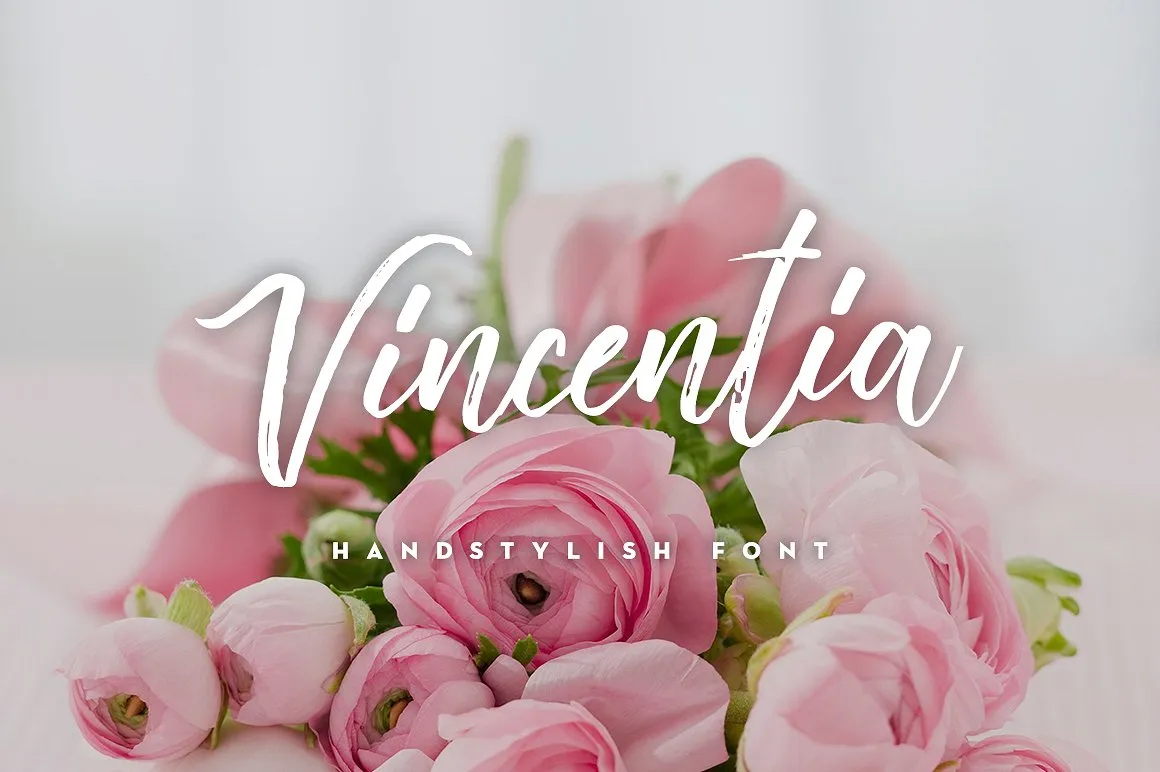
Vincentia Handstylish Font – Download Grátis
Vincentia Handstylish Font é uma nova adição à família de fontes brush do Alif Devan R., desenhada para atender a necessidades criativas. Ideal para logos, cabeçalhos, títulos e impressões, ela também se destaca para processos criativos em geral. Desenvolvida com um estilo autêntico e natural, Vincentia oferece uma textura única que torna qualquer projeto impecável. Com o uso de Vincentia Handstylish Font, você pode criar resultados extraordinários com um toque autoral incrível. Perfeita para aquelas idéias inovadoras que requerem uma cara única e alegre, ela é perfeitamente adequada para aqueles projetos que valorizam tanto a elegância quanto o design único da mão. Seja você um artista gráfico em busca de uma fonte única ou um designer profissional desejando dar um toque especial aos seus designs digitais, Vincentia Handstylish Font está aqui para ajudar a trazer vida e personalidade a cada projeto.